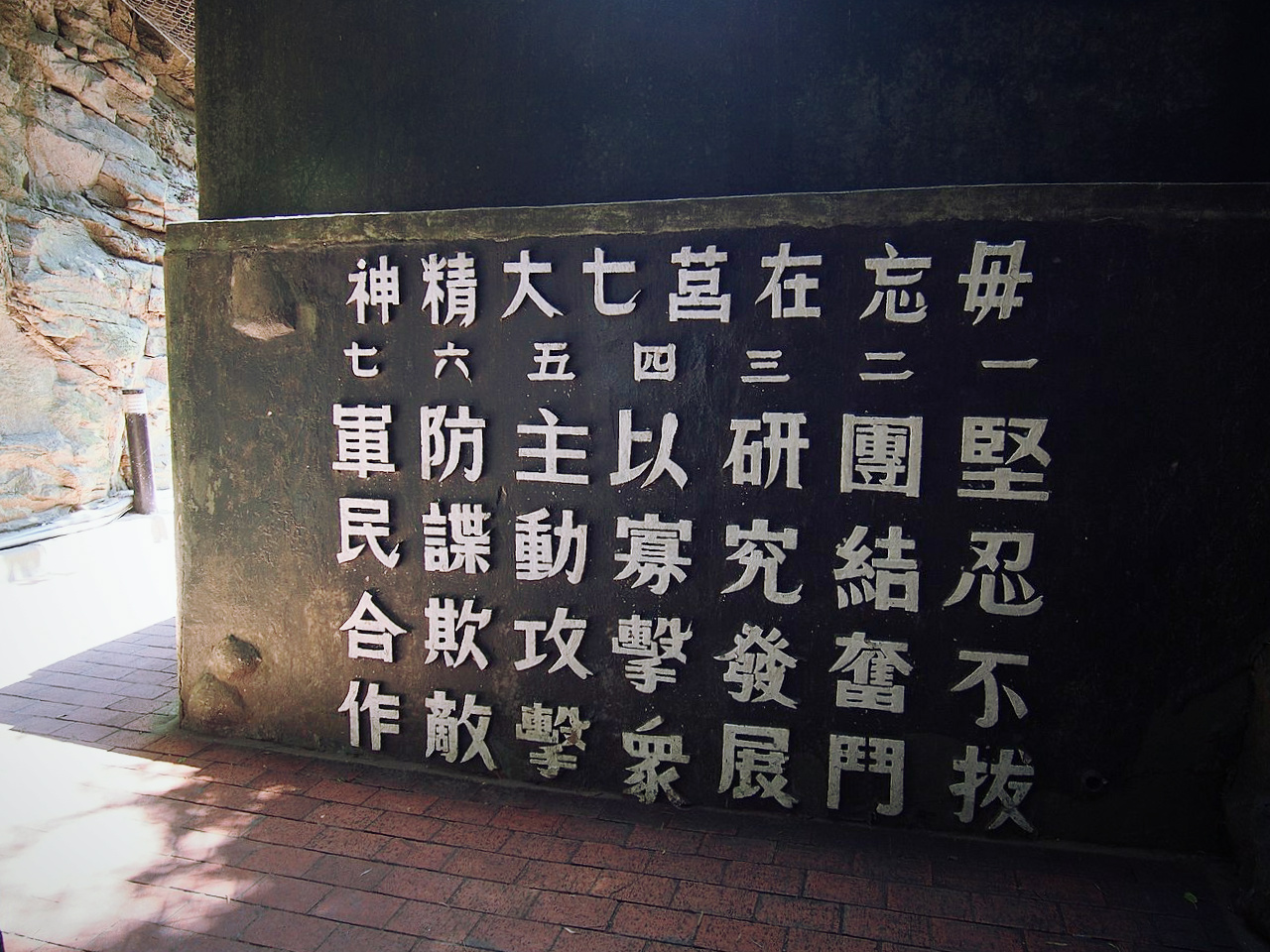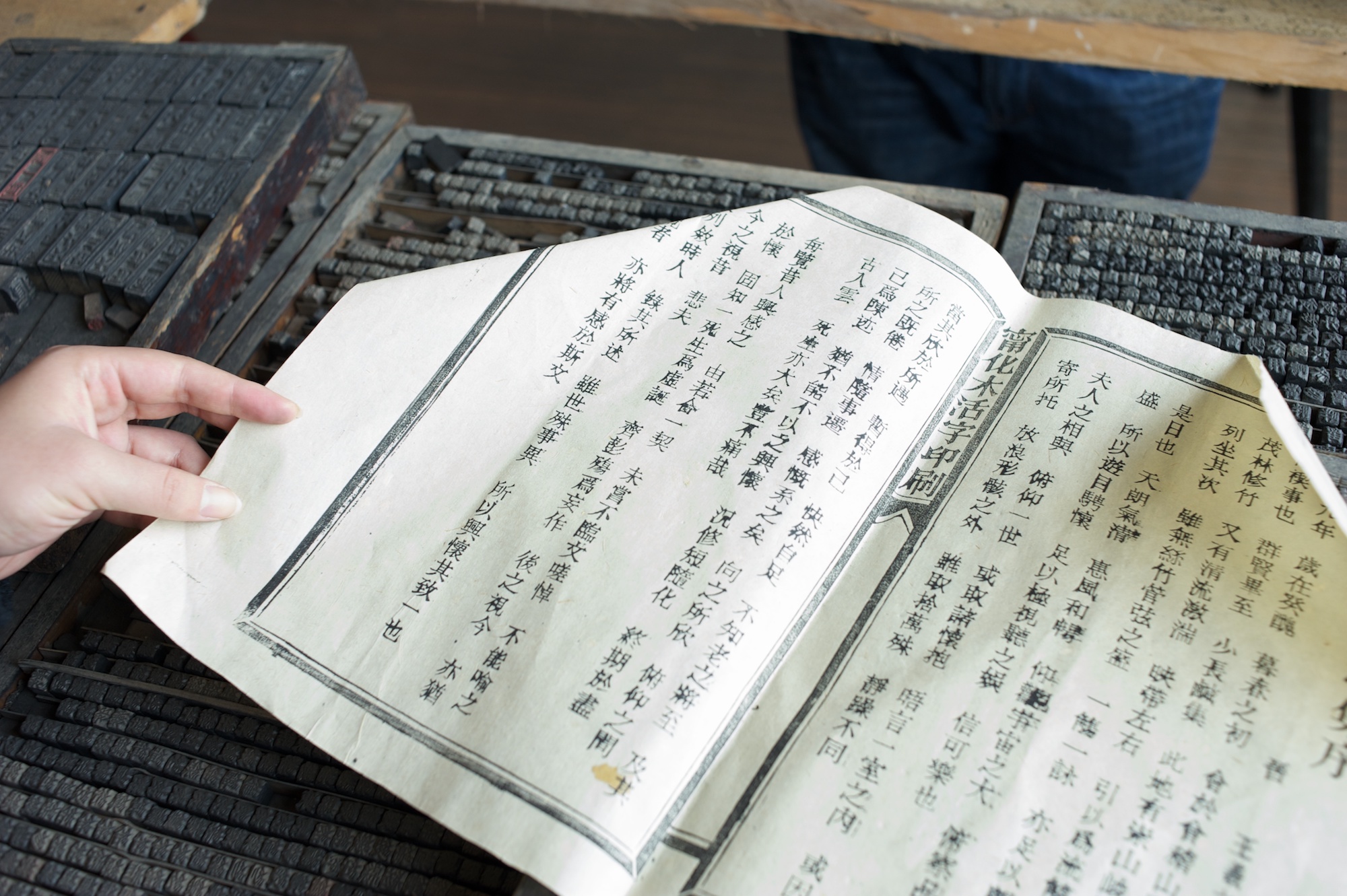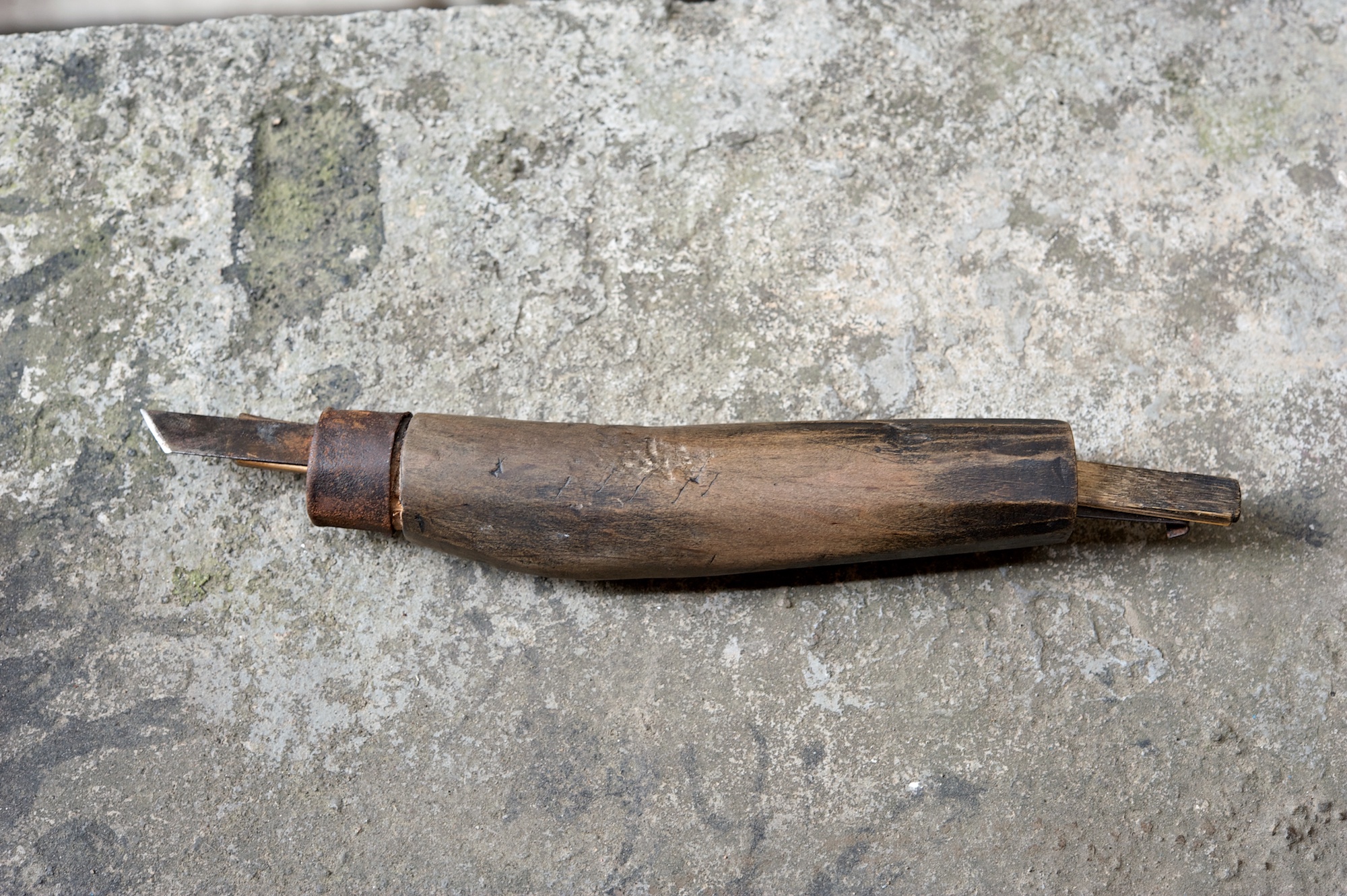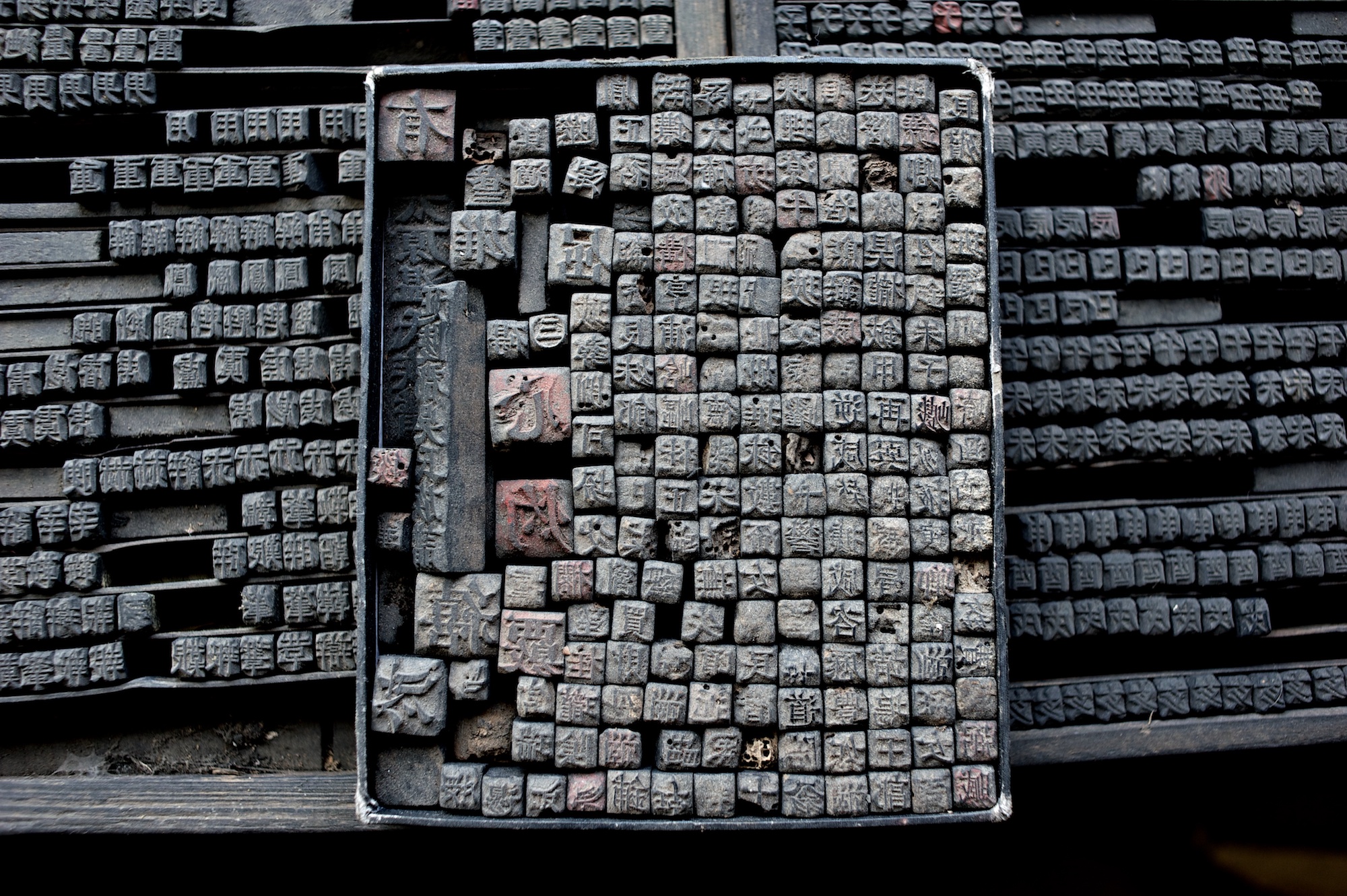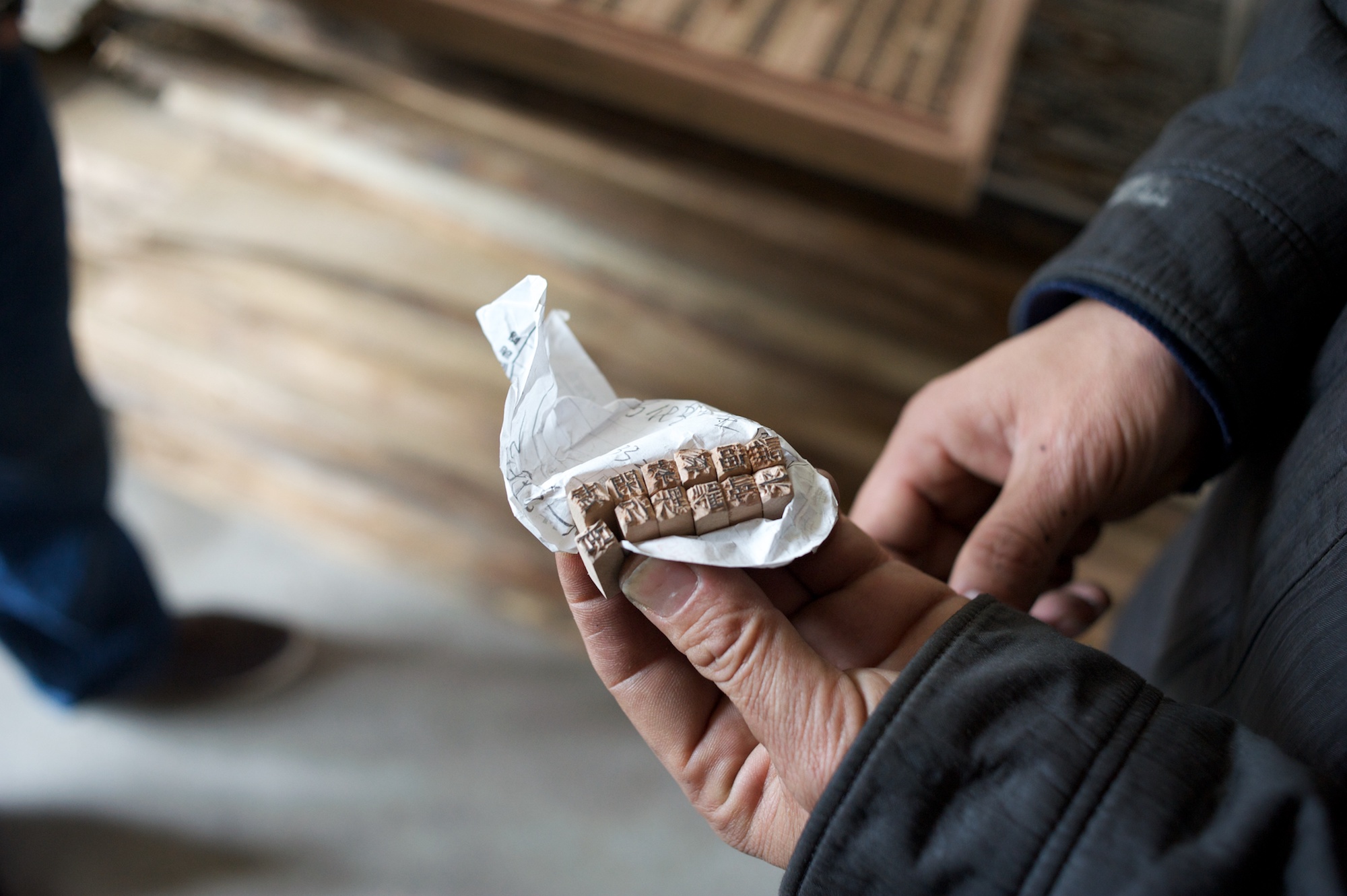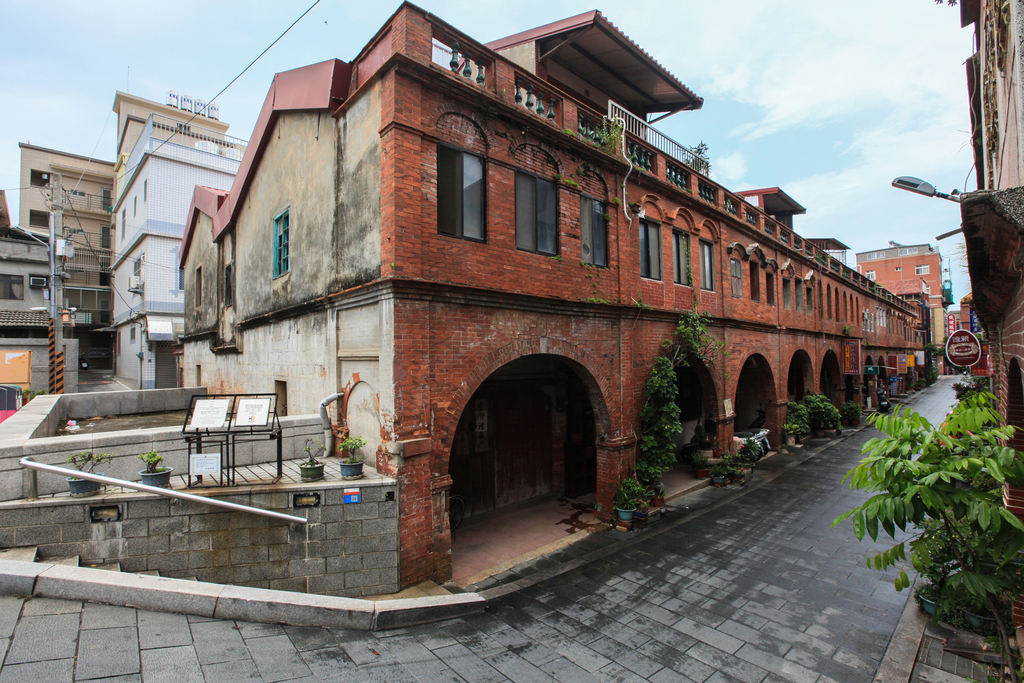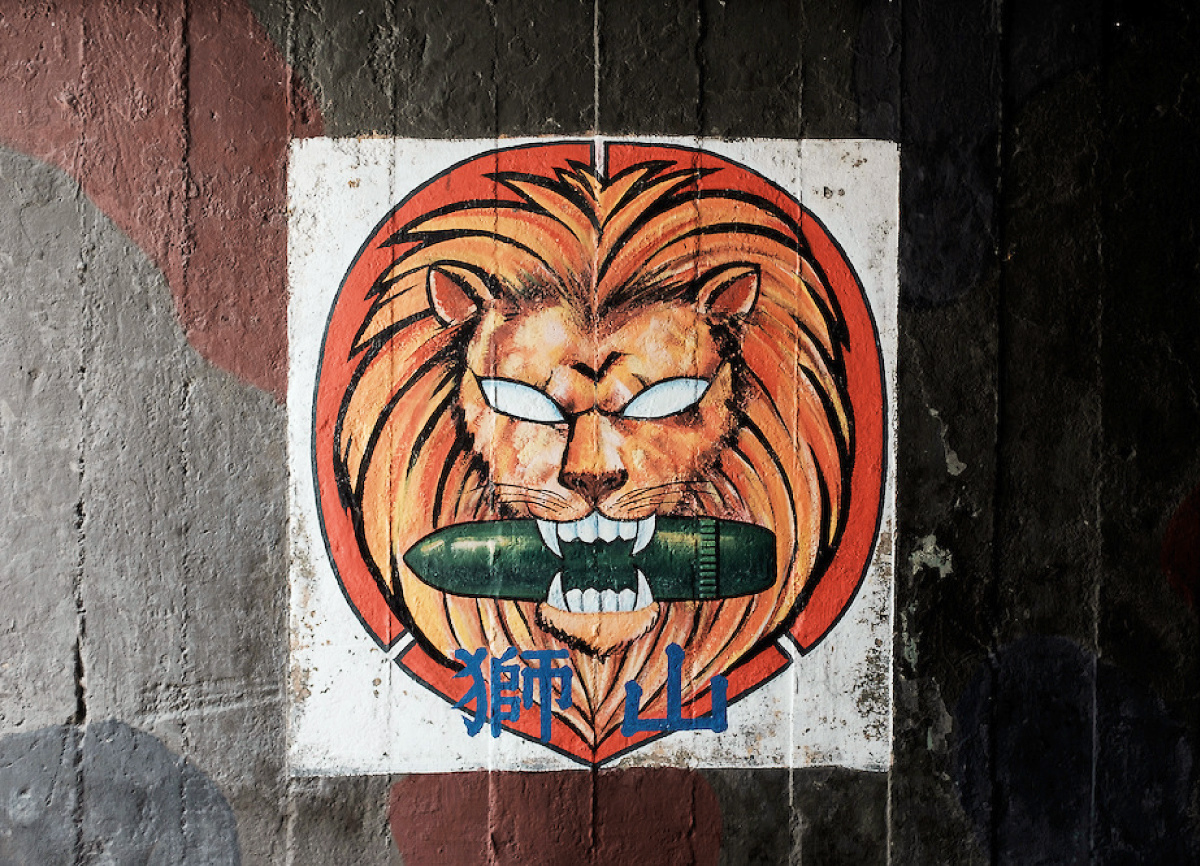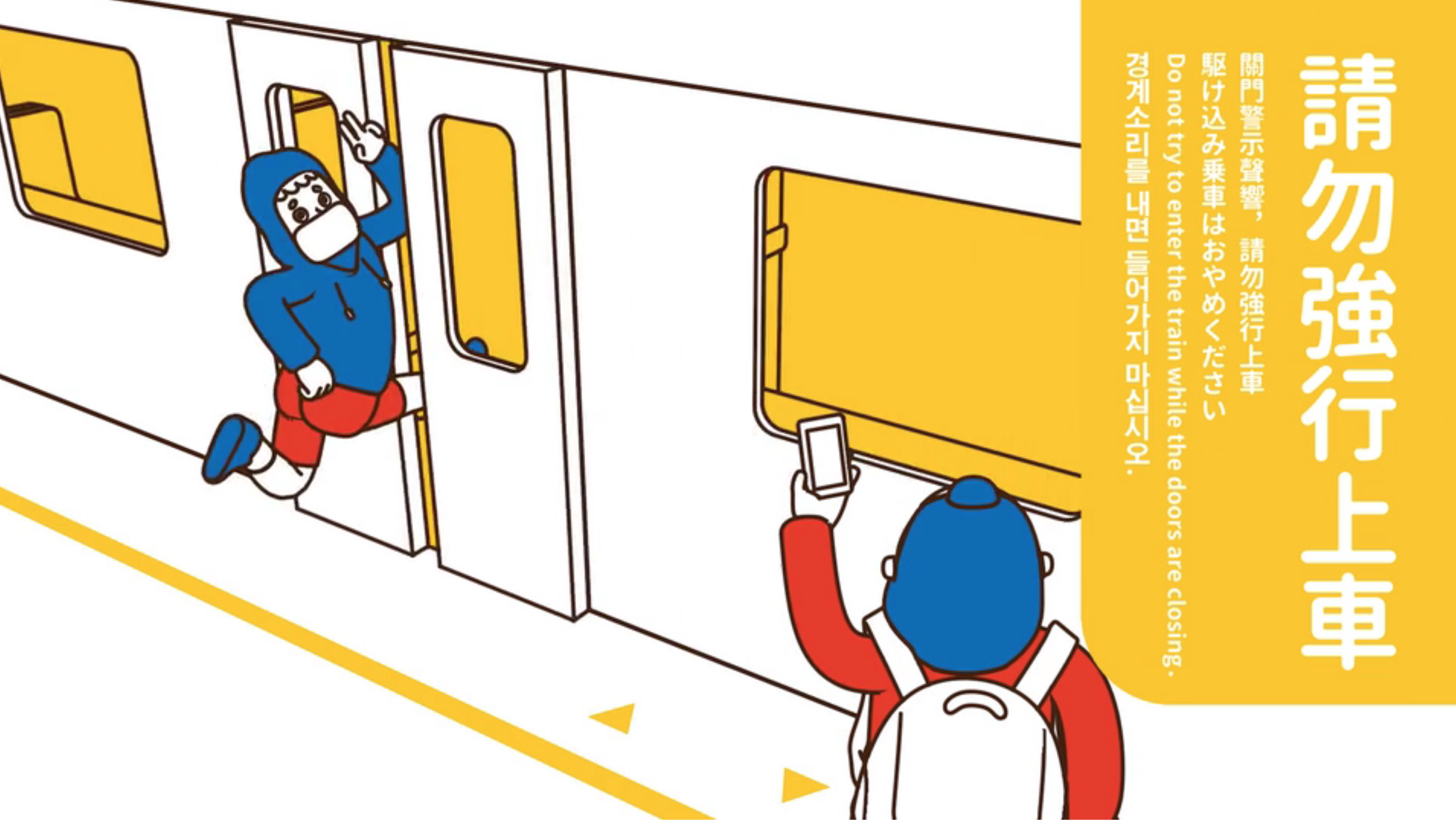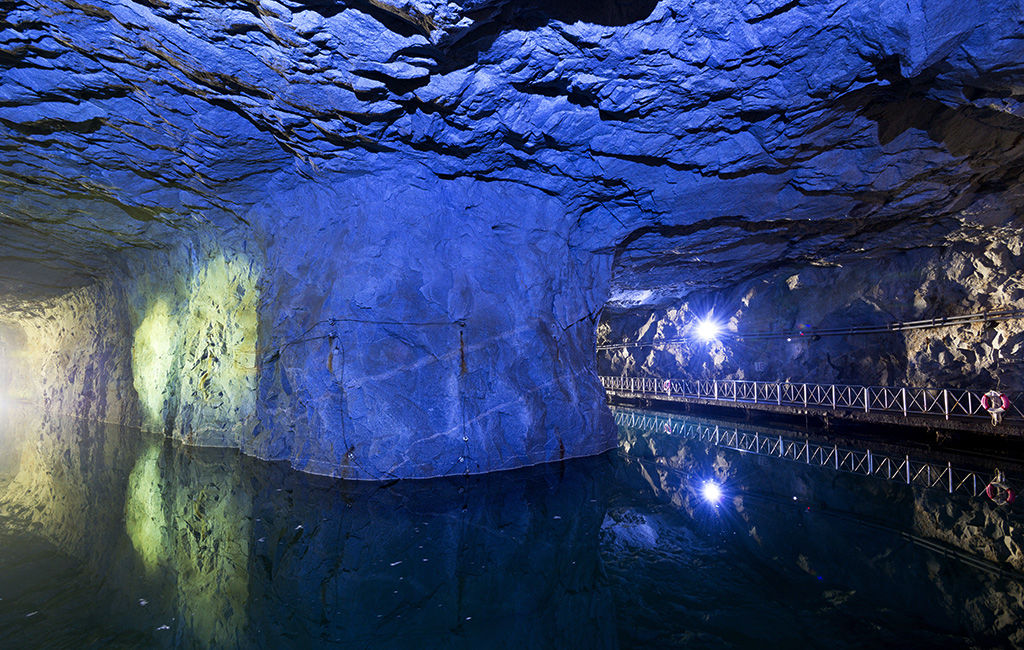
招募!TypeTour 台湾字体文化之旅——金门、台北(2018.2.25 – 3.3)
新年伊始,TypeTour 计划再去一次亲切又陌生的台湾。这次我们将从厦门出发,渡过浅浅的海峡,从金门登陆,再飞往台北。
隔海相怼的宣传口号,军事设施中的历史遗迹,还有闽南古厝、传统聚落、风情洋楼,与邓丽君、小确幸、高粱酒,共谱一首绿岛小夜曲。从海岛飞抵台北,一下子进入繁华的大都会。深藏老城中的铸字行与刻字铺;年轻一代台湾设计师的面对面交流;走九遍都不厌的忠孝东路;为民艺发声的汉声巷;大陆学习样板的各大文创园;以前只是听说的传奇字体公司与出版社;24 小时不打烊的诚品书店;「文恐份子」的城市漫游导览……
TypeTour 与普通的主题旅游项目不同,我们希望聚集更多对字体排印、平面设计、视觉文化感兴趣的朋友们,在旅行的同时促成更有价值的交流。本次字体旅行,我们将在保持参观访问质量和数量的前提下,留出充分的自由活动时间,让参与者拥有更多自主探索的机会,二位领队也会根据团员的需求,给出针对性的建议。
行程安排
- DAY 1( 2 月 25 日):莒光楼、金城模范街、翟山坑道、狮山炮阵地、山后民俗文化村;
- DAY 2( 2 月 26 日):陈景兰洋楼、邓丽君纪念馆、阳翟聚落、从金门飞往台北;
- DAY 3( 2 月 27 日):「总统府」、日星铸字行、柏祥号刻字铺、大稻埕;
- DAY 4( 2 月 28 日):松山文创园、不只是图书馆、汉声巷、诚品书店、迪化街;
- DAY 5( 3 月 1 日):行人文化实验室、卵形工作室 / 田修铨、justfont & 字恋小聚;
- DAY 6( 3 月 2 日):文鼎科技、淡水老街;
- DAY 7( 3 月 3 日):自由活动、经金门返程回厦门。
详细行程
DAY 1
莒光楼 为表彰在古宁头战役和八二三炮战中的「中华民国」国军官兵于 1952 年所建的莒光楼,曾作为「中华民国」邮票的图案传布全球,驰名国内外,成为许多国内外宾客访金的第一站。是战地金门的精神象征,也是国共对峙、全球东西阵营冷战对峙的地标。
金城模范街 是为 1924 年由时任金门县商会会长傅锡琪与地方绅士翁同文决定为金门建起一条「足以为模范」的街道。建筑风貌具日本、闽南、西洋、南洋等各种风格。建筑多为二进店屋,第一进为日式洋楼,第二进为闽式建筑,是金门维持许久的老街之一,也曾是郑成功训练陆军的「内校场」。(老街的国共餐厅还有传说中的「毛泽东奶茶」……)
翟山坑道 A 字型战备水道,1961 年因应战争所需而开挖,由人工一凿一斧耗时5年开凿而成,供战时登陆小艇抢滩运送补给。坑内建有停靠码头。坑道外海浪澎湃,潮声势壮。后因金门岛功能减退,于 1975 年废弃;由金门国家公园管理处接管维护并于 1987 年正式向民众开放观光,成为金门县重要的观光景点。
狮山炮阵地 狮山炮阵地始建于 1965 年,当年主要负责金门东北部海域的安全,是坑道炮兵阵地的代表作。坑道内设有 8 寸榴弹炮、75 山炮、各式火炮底火筒展示区和「狮山炮阵地及榴炮发展」影片欣赏。参观时运气好还能遇上全台湾唯一的炮阵军事训练演习。
山后民俗文化村 知名的「金门民俗文化村」建于清光绪 26 年(1900 年),是金门第一个开放成为观光景点的聚落。此聚落由赴日经商致富的王国珍及王敬祥出资兴建,特别聘请江西建筑名师设计,从每户位置、用途到室内空间、庭院、阁楼等,乃至壁梁雕画、装饰泥塑取材,都相当考究,历时 25 年完工。这 18 栋古建全部依山面海、井然有序,分三排排列,呈现出精致而完整的闽南建筑风貌。
DAY 2
陈景兰洋楼(陈坑大洋楼) 始建于 1917 年,1921 年完工,由金门陈坑人(现称成功)陈景兰先生出资建造,落成后部分楼房做为尚卿小学,特别由厦门鼓浪屿聘请老师,任用陈文温为校长,供陈坑当地人免费就学,造就了成功村「一门三博士」的美话。陈景兰洋楼曾经被作为医院、中学和官兵休假中心使用。
邓丽君纪念馆(迎宾馆) 迎宾馆 1980 年完工,是金门战地政务时期最著名的外宾接待所,更有「地下希尔顿饭店」的美名,军管时代,是金门接待外宾的住所,经过数年整修后,现已成为邓丽君纪念馆,馆内摆着邓丽君数次金门劳军的照片,影片供游客观赏,馆外还有邓丽君到金门劳军与阿兵哥同乐的雕像。
阳翟聚落 阳翟老街位于金门东北部的金沙镇,是一个已经具有千年以上历史的聚落,早期以发展盐业而立村。在过去有「金门小西门」之称,也是电影《军中乐园》的取景地。「八二三」炮战后,阳翟成为军事重镇,许多主要以服务阿兵哥的设施纷纷设立,但随后由于军事精简,阳翟的繁华如潮水般逐波退去,如今留下的只有当时店家招牌上斑驳的手绘字体与墙面上的军事彩绘供人了解当初国军的生活画面。置身于阳翟聚落仿佛电影搬的场景中,一切宛如时光逆转。
从金门飞往台北。
DAY 3
「总统府」 「中华民国总统府」厅舍,为「中华民国总统」、「副总统」、及「总统府」相关单位的办公场所,也是每年元旦及「国庆日」举行升旗典礼的地点。厅舍建于 1919 年,建筑风格属「后期文艺复兴式」,二战后经过整修,是台湾政治中枢的重要建筑,具有特殊的时代意义。
日星铸字行 成立于 1969 年的日星铸字行,专门生产金属活字,以提供给印刷行业。中南铸字厂于 2000 年关闭后,日星铸字行成为台湾唯一仅存的金属活字工厂,厂内库藏三十余万字的中文铅体与字模。四十余年不间断,以火铸造铅字,在光与电的现代社会中,守护属于台湾的遗产。同时,日星铸字行与中央研究院数位文化中心合作,耗时两年多,成功把堪称华人世界最后一套的「繁体中文铅字字体」数字化,成立专属网站、做成字型档提供给民众下载,命名为「日星初号楷体」,也使得日行铸字行成为台湾字体文化交流重要的平台。
柏祥号刻字铺 柏祥号刻字铺从日治时代开业至今已经是第三代,铁皮刻字就是在铁皮上用凿子将铁皮依照设计的字型挖空,再以喷漆将凿出的字型显现在物体上。早期贸易繁忙的年代,这项技术曾经广为应用与茶行货箱的信息喷涂中。在大稻埕早期凡是有货物要出口,这些公司行号就会向柏祥号刻字铺下单。随着时代与环境的变化,喷字需求大幅下降,柏祥号成为大稻埕目前仅存的刻字铺,在民乐街巷弄中默默守护逐渐失传的工艺。往期几乎每一位去过柏祥号的团员都会请老师傅亲手打一块刘体楷书或镂空西文的铁板留作纪念。
大稻埕 大稻埕为台北市汉人的早期聚居地之一,兴起于 1854 年,因为清朝对外条约的关系,成为国际贸易港口而掘起。在日治时期,被称作「台北三市街」之一。直到 1990 年代以前,都是台湾国际贸易最为兴盛的地区。同时,也是台湾近代化建设、引入国际思潮的起源地。此地区在 1990 年代末期至 2000 初期,开始出现历史街区保存的概念。至今,此区有大量的政府登记在案的文化资产。我们将带领大家走逛大稻埕,从老街的店名与匾额、政府规划的制式招牌、新式创意小店的店招,还有传统庙宇内的各式文字,来看台湾的文字应用设计。晚上,我们将于知名观光夜市——宁夏夜市用餐,同时观察台湾对于饮食文字的应用(招牌与菜单)。
DAY 4
松山文创园 松山文创园区建于 1937 年,前身为台湾日治时期「台湾总督府专卖局松山烟草工场」(因此当地人简称其为「松烟」)。1998 年停止生产,2010 年正式转型定名「松山文创园区」。园区全区为古迹建筑,制烟工厂、仓库建筑古色古香保存完善,是近年国内外艺文展览办展的热门场地。除了提供展览空间,松山文创园区也推出自办活动,包括总结台北市年度原创能量的原创基地节、学生毕展主题月松山文创学园祭,并且推出与公协会合作的 133 号合作社以及主打实验性展演的 LAB 创意实验室。
不只是图书馆 由台湾创意设计中心营运,位于著名的松山创意园区,是台湾首座专业设计图书馆,拥有超过 20,000 册丰富的藏书、超过 100 种国内外设计杂志。图书馆的空间设计由建筑师姚政仲操刀,保留古迹的个性,大面积的老窗户包容了温暖的光线,室内则使用了黑色金属框架与深色玻璃,在理性而静谧的秩序感中,带给读者宽敞又舒适的感受。图书馆以「不只是」为主轴,不定期推出「不只是 3×3」主题展览、举办近距离迷你讲座、推出品牌系列活动等等。
汉声巷 《汉声》杂志成立于 1971 年,是台湾地区报道中国传统民间文化的一系列主题书,创办几十年来,一直采用田野实际调查兼图片、摄影并陈的手法,记录下中国偏远山村中蕴藏的许多丰富多彩的民俗文化。一直致力抢救、保护和发扬中国民间传统文化,亲力奔走于民间,完成大量民间文化的收集和整理,拯救数十种濒临失传的民间手工艺。长期收集建立起「中国民间文化基因库」,出版杂志 140 多期,内容涉及民间文化、民间生活、民间信仰、民间文学、民间艺术等若干方面。出版社藏身在平实的台北八德路巷弄里,取名为 「汉声巷」,是以民俗学家送给汉声人的 「村店出好酒,陋巷有高才」 自许,继续在这条巷子里为守护民间传统文化、儿童教育而努力,运气好的话还能偶遇上《汉声》的创办人黄永松先生。
诚品书店 台湾大型综合性书店,同时结合商场经营,旗下事业涵盖百货零售业、文化艺术、旅馆与不动产经营等。在台北开有敦南、信义、台大等店,诚品书店信义店是全台湾规模最大的复合式书店,结合阅读、艺文活动与创意生活为一体。在这里可以在这参加新书发表、表演艺术、讲座等各式交流活动;加上充满文艺气息的商场、地下室,还有美食街,是历次 TypeTour 团员驻足无法离开的地方,完全可以在这里逛上一天不出来。
迪化街 迪化街初建于清朝咸丰年间(1850 年代),19 世纪末以来一直是台北市重要的南北货、茶叶、中药材及布匹的集散中心。「迪化」一名,是 1947 年中华民国政府投射当时新疆省省会迪化市(今乌鲁木齐)所制定的街道名。1996 年开始,保存原状的迪化街除了成为台北市最古老街道外,也于每年农历春节前夕扩展成规模盛大的「台北年货大街」。不仅如此,迪化街也同样维持相同的批发商业功能。除了高达 70 栋以上的老式传统建筑可供欣赏外,还有位于南街与中街间的大稻埕霞海城隍庙也颇具盛名。